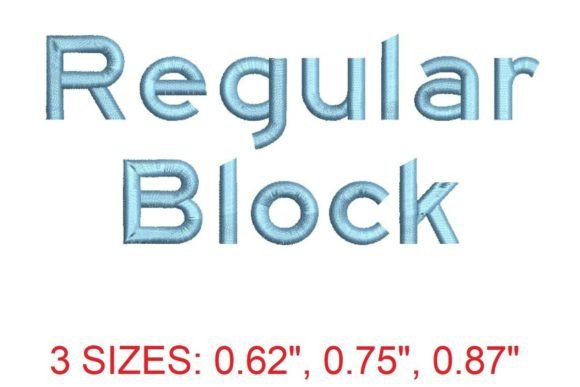
Regular Block Embroidery Font
De Regular Block Embroidery Font is een toonbeeld van elegantie in eenvoud. Deze font, ontworpen met een minimalistische aanpak, biedt een schitterende balans tussen functionaliteit en stijl. Perfect voor wie op zoek is naar een lettertype dat zowel tijdloos als intuïtief te gebruiken is, maakt deze embroidery font het gemakkelijk om je creatieve projecten een professionele en verfijnde touch toe te voegen.
Bouwkwaliteit en technische details
Met zijn heldere, duidelijke lijnen en uitstekende leesbaarheid, onderscheidt de Regular Block Embroidery Font zich door zijn robuustheid en consistentie. Het lettertype is geoptimaliseerd voor gebruik in verschillende maten, waardoor het perfect is voor zowel fijn gedetailleerde werkjes als grotere, meer prominent gepresenteerde teksten. De kwaliteit van het vervaardigingsproces staat garant voor een soepele integratie in diverse embroidery software, zonder dat er sprake is van afbreking of verwarring in de details.
Voor wie is dit product het beste?
De Regular Block Embroidery Font is ideaal voor beginners en ervaren naaisters die waarde hechten aan eenvoud en klassieke stijl. Of je nu bezig bent met het personaliseren van kinderkleding, het maken van unieke huishoudelijke artikelen, of het toevoegen van een naam of speciaal bericht aan een geschenk, dit lettertype past bijna overal. Het is ook zeer geschikt voor zakelijke toepassingen, zoals het merken van werkkleding of het creëren van herkenbare branding elementen.
Tip van de expert: Combineer de Regular Block Embroidery Font met subtiele kleurvariaties of textuurtoevoegingen om een extra dimensie aan je projecten te geven, zonder de eenvoud van het ontwerp te verliezen.
Hoe het zich verhoudt tot de concurrentie
Tegenover andere embroidery fonts op de markt, zoals complexe script- of decoratieve fonts, biedt de Regular Block Embroidery Font een adem van verscheidenheid en toegankelijkheid. Waar sommige alternatieven moeilijk kunnen zijn om mee te werken vanwege hun gedetailleerde aard, biedt deze font een eenvoudige, directe aanpak die niet alleen tijd bespaart, maar ook een schoon, professioneel resultaat garandeert. Dit maakt het een must-have voor iedereen die op zoek is naar een betrouwbare, eenvoudige oplossing.